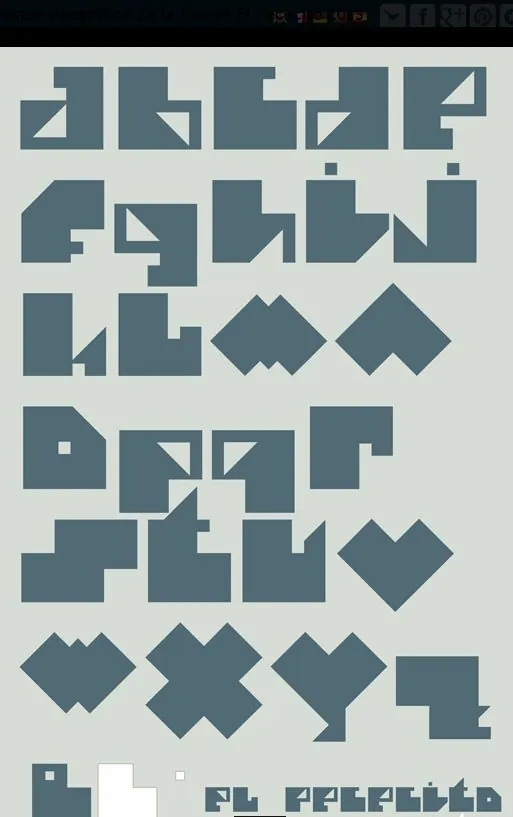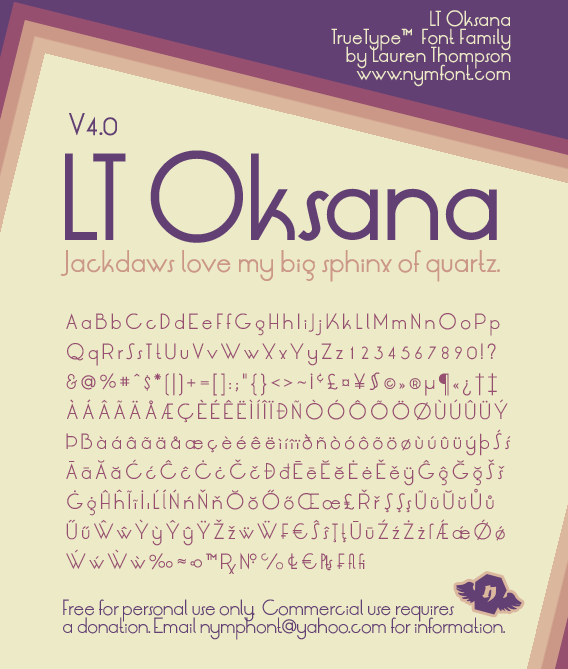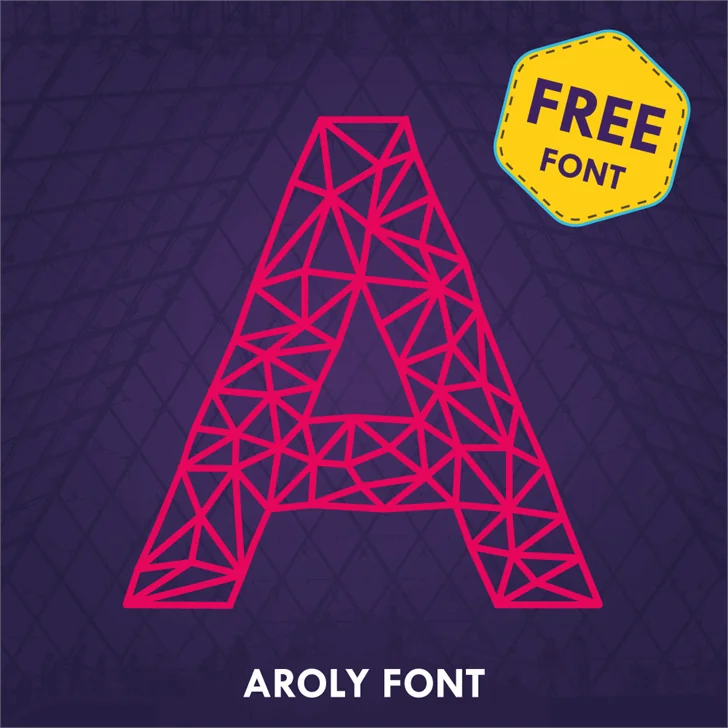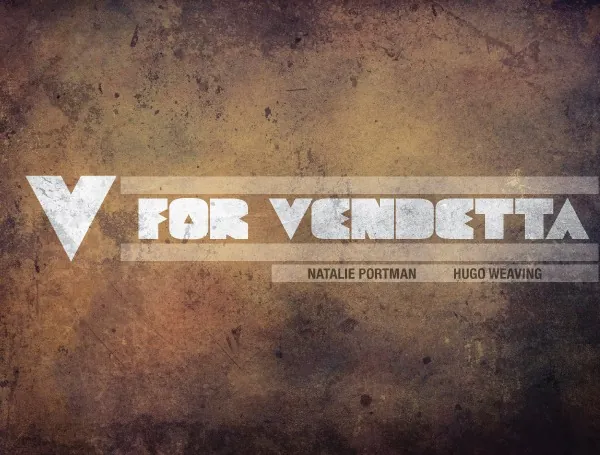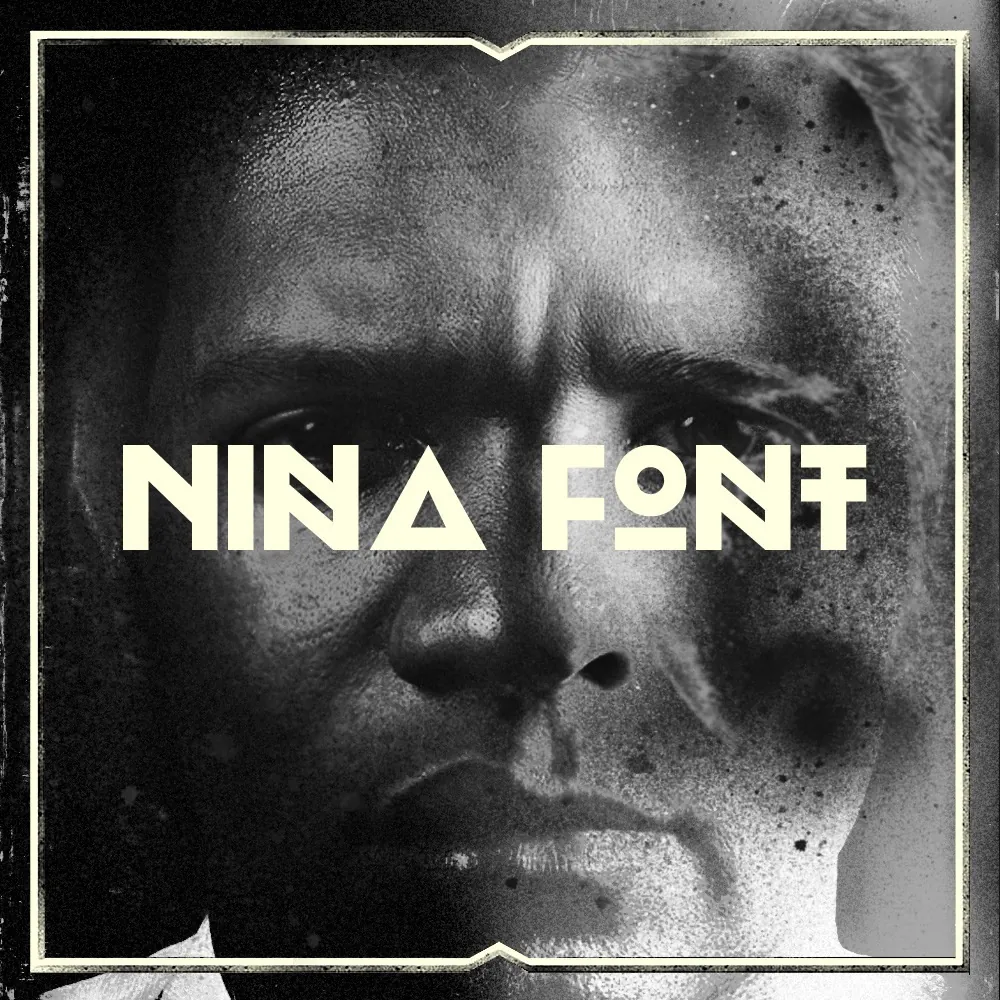
Hay fuentes que engrandecen los diseños. En el artículo de hoy te invito a ver una colección de tipografías geométricas que podrás incluir en tus trabajos. Te las puedes descargar gratis.
Si estás buscando las típicas tipografías de palo seco geométricas te recomiendo que busques una Futura, Avant Garde o Kabel, aquí te propongo fuentes geométricas en el sentido amplio de la palabra. Encontrarás algunas de palo seco pero no todas serán de ese estilo.
El pececito
Geometric PW
Aroly
Es una tipografía poligonal que consigue un diseño original.
Geometric Black
Fuente muy ancha, que quedará genial en títulos de posters. Es una tipografía sans serif que te podrás descargar gratis.
Geometric Shadow PW
Nina Font
LT Oksana
Es otra de estilo de palo seco.
Champagne & Limousines